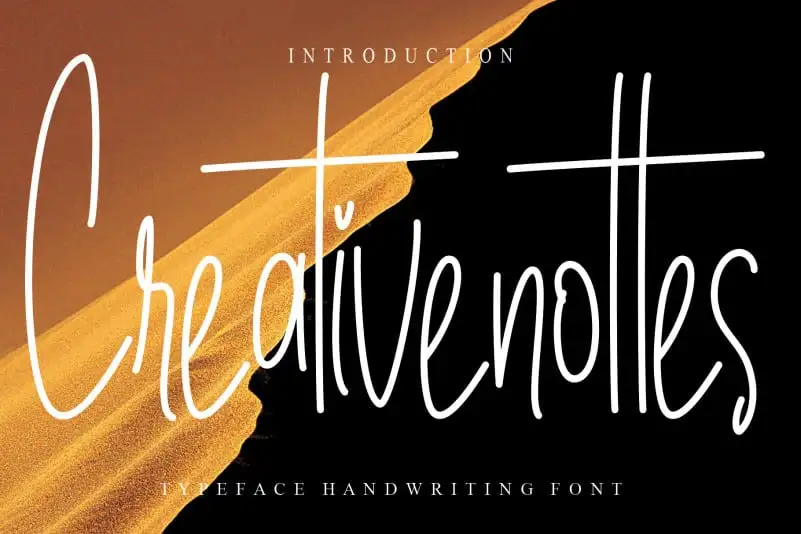
Creativenottes Handwritten Font
A fonte Creativenottes Handwritten Font é uma escolha perfeita para quem busca um toque autêntico e envolvente em seus projetos digitais. Inspirada na arte do desenho à mão livre, essa fonte apresenta linhas finas que transmitem delicadeza e profundidade, criando texturas sutis e harmoniosas. Perfeita para design gráfico, ilustração digital ou criação de arte digital, a Creativenottes Handwritten é uma opção ideal para quem busca um estilo elegante e sofisticado sem deixar de lado seu caráter autêntico e criativo. Como se fosse uma conversa entre amigos, essa fonte transmite sentimentos e emoções através dos traços fluidos e suaves da escrita à mão livre, oferecendo aos criadores um recurso poderoso para personalizar seus projetos de design digital.